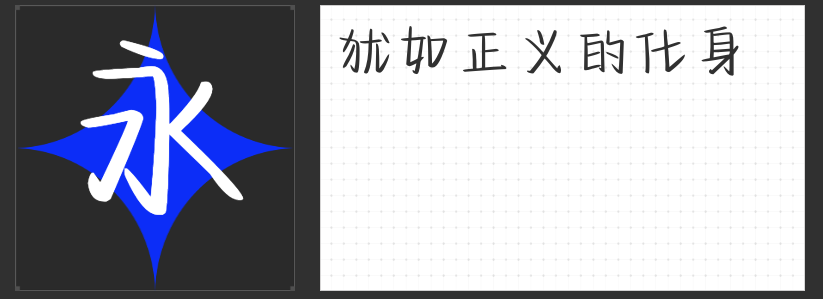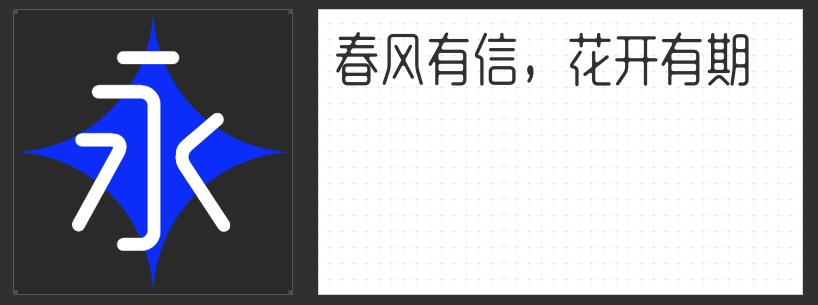
短视频视觉进阶指南:四款高适配字体的风格化表达
短视频时代,字体不仅是信息载体,更是情绪传递的视觉符号。以下四款专为屏显优化的字库字体,以独特的造型语言与动态适配性,为短视频内容注入鲜明的视觉基因。
一、励字超级勇士简 微粗
作为通用黑体的进化版,这款字体通过外圆角设计打破传统黑体的机械感——笔画拐角处微弧处理,既保留了黑体的稳重骨架,又赋予字形灵动的呼吸感。其字面宽大、结构紧凑的特质,在快速滚动的信息流中保持清晰可读性,尤其适合作为标题或重点信息呈现,在严肃叙事与轻量化表达间找到平衡点。
二、高手庆科静雅体 瘦版
以瘦长字型构建视觉纵深感,这款字体通过均匀布白与重心校准实现“瘦而不倒”的视觉效果。小连笔设计弱化了生硬转折,圆角处理让笔画如流水般自然衔接,去钩处理则进一步简化视觉负担。其克制的设计语言,既能承载知识类内容的理性气质,也可适配生活类视频的清新调性,成为短视频中“隐形的美学框架”。
三、励字铁拳简 超级黑
粗壮笔画与宽大字面构成强烈的视觉冲击,这款创意黑体以“铁拳”为设计隐喻——饱满的块面感传递笃定态度,折角圆润设计避免生硬感,在力量与亲和力间达成微妙平衡。其高辨识度的造型适合作为品牌标语或情绪爆发点的视觉强化,尤其在运动、科技等需要强化张力的内容场景中,能瞬间抓住观众注意力。
四、字圈也字综艺弹幕体
专为弹幕场景设计的这款字体,以倾斜结构与棱角游戏打破静态平衡——横竖笔画左低右高的走势制造动态错觉,钝角与直角的交替使用强化节奏感,圆润与尖锐的矛盾处理暗合年轻群体的叛逆审美。其不拘一格的造型语言,既能承载吐槽文化的幽默基因,也可为音乐、游戏类视频注入亚文化态度,成为Z世代观众的情感共鸣点。
四款字体,或以克制美学提升信息密度,或以夸张造型强化情绪表达,通过精准的屏显适配与风格化设计,为短视频创作者提供从工具到艺术的升级方案。